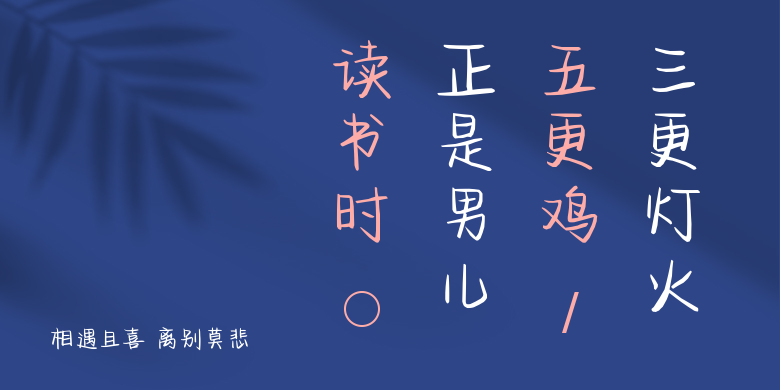
相遇且喜 离别莫悲
相遇且喜 离别莫悲,这款字体结构工整、笔画清晰,兼顾美观与易读性,适用于标题、正文、海报、包装、LOGO 等多种场景。字形优雅稳定,风格百搭耐看,适配日常排版与创意设计,让文字呈现更舒适、更具质感。相遇且喜 离别莫悲一笔一画,皆是细节,以均衡的比例、流畅的线条打造舒适视觉体验,字形端正大气,风格简约现代。无论是商业设计、品牌宣传还是日常排版,都能轻松驾驭,让文字更有格调与力量。相遇且喜 离别莫悲字体下载。